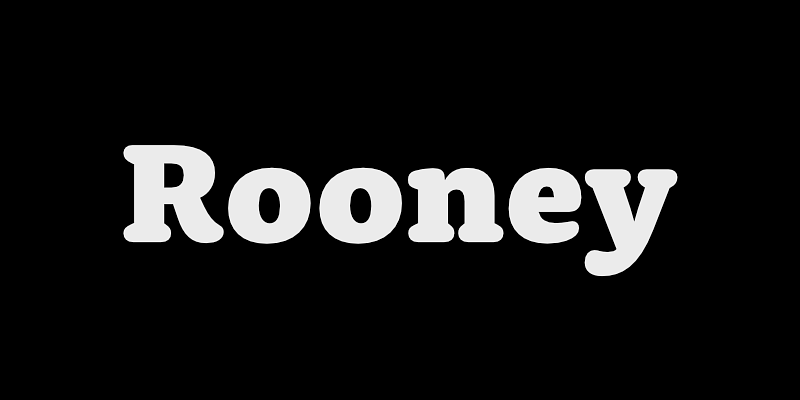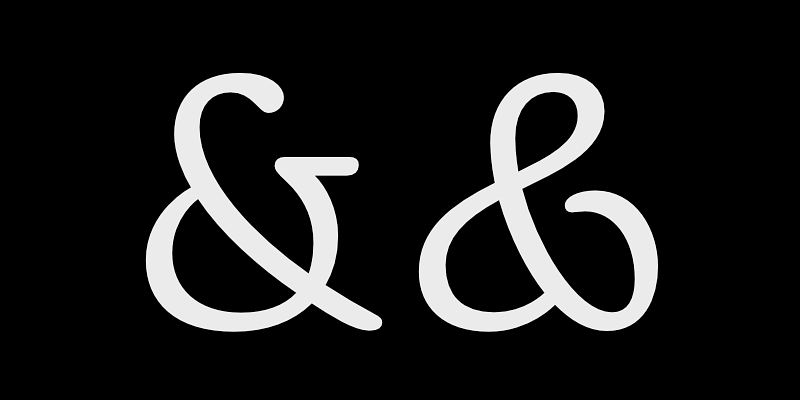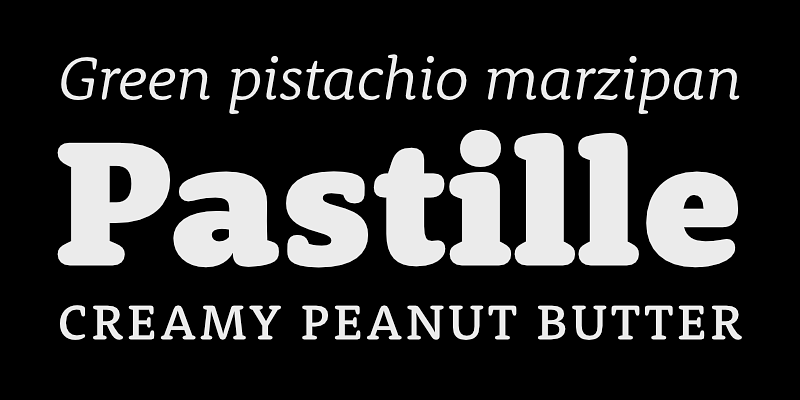
Rooney basiert hauptsächlich auf den Konstruktionsprinzipien einer Serifenschrift alten Stils. Sie kombiniert zwei verschiedene Ansätze: Sie hat unverwechselbare, originelle Buchstabenformen, ist aber dennoch sehr gut lesbar und vielseitig.